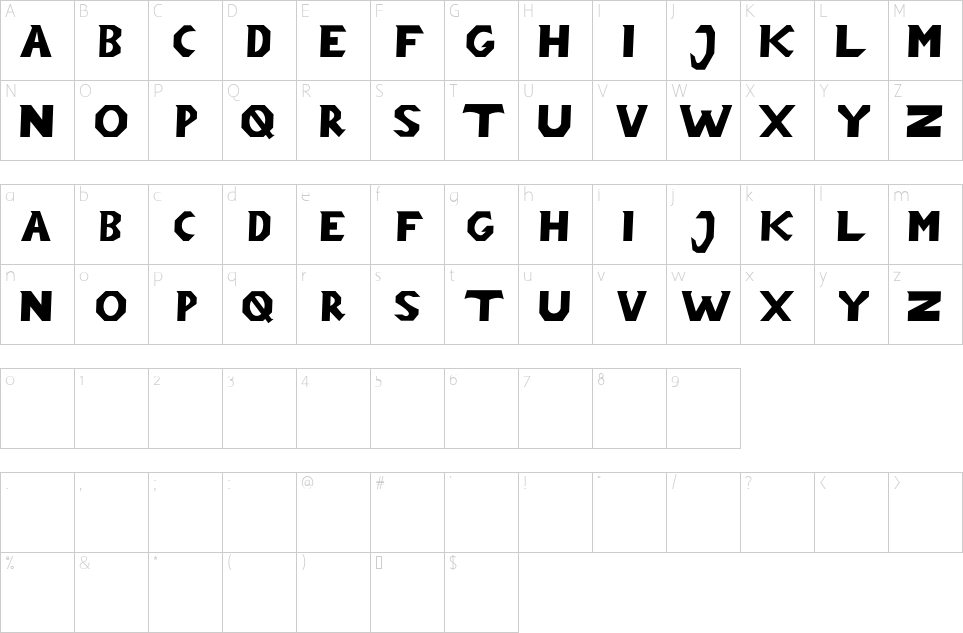
A Montire é uma fonte elegante e versátil que se destaca na categoria de fontes gratuitas. Desenvolvida pela Craft Supply Co, esta fonte vem com uma variedade de estilos que se adaptam perfeitamente para diversas aplicações, desde design editorial até identidades digitais. A Montire traz uma combinação harmônica de linhas elegantes e sutileza, proporcionando textos profissionais e amigáveis para leitura. Ideal para quem procura uma fonte confiável que se adapte às mais diversas necessidades, a Montire é um ótimo complemento para qualquer projeto de design. Com seus 303 downloads, a Montire provou sua capacidade de oferecer uma solução eficaz e versátil para quem busca fontes gratuitas.